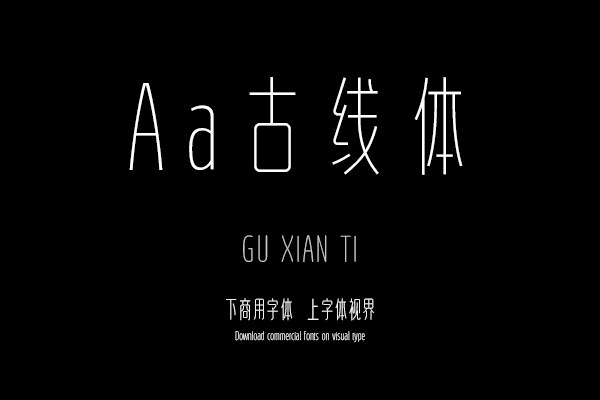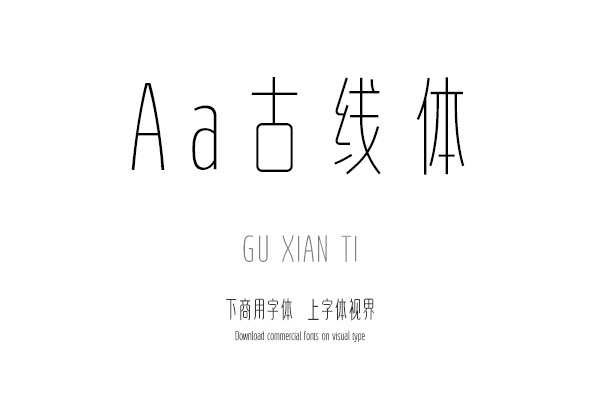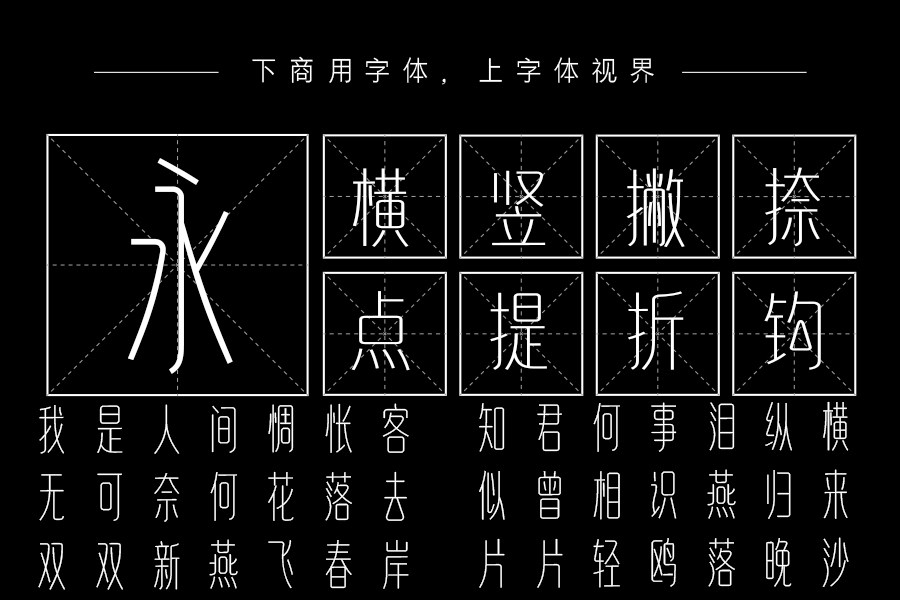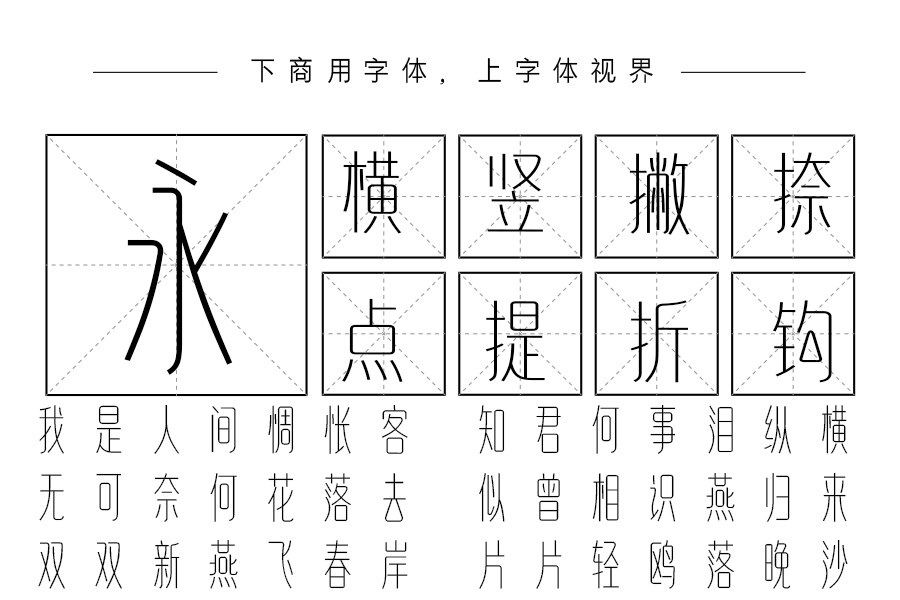
取篆书笔画设计的修长等线字体,曲线干净简约,气质兼容古典与现代。购买须知:“下载服务费”与“字体VIP”所获得字体 仅用于个人非商用, 商用请联系付费授权。本字体为电脑用字,手机没有root权限不支持直接手机换字(手机如何root,请自行百度搜索教程)。购买前请先 了解清楚后再付款 ,字体为虚拟产品无法回收 一旦购买不支持退款。